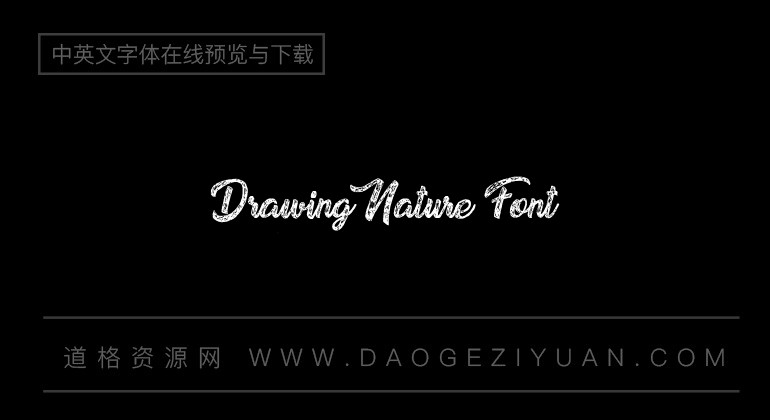
Drawing Nature是一种手绘风格的字体,适用于各种自然、户外和生态主题的设计项目。这种字体的特点是它的字母外形仿佛是由钢笔或毛笔画出来的,给人一种手工制作的感觉。字体的线条柔和,轮廓清晰,适合用于海报、标志、包装等多种设计项目。 Drawing Nature字体包括大写字母、小写字母、数字和一些标点符号,每个字符都具有独特的手绘风格。该字体还提供了多种风格和变体,让设计师可以在不同的情境中使用它。 总之,Drawing Nature是一种适用于自然、生态和户外主题的手绘风格字体,可以为设计项目带来独特的感觉和风格。内容介绍
Drawing Nature Font是一款非常不错的手写艺术字体,具有很好的视觉感,适合于文化类的宣传设计、商业类品牌的广告和产品包装设计以及个性化文字排版等较多场景。